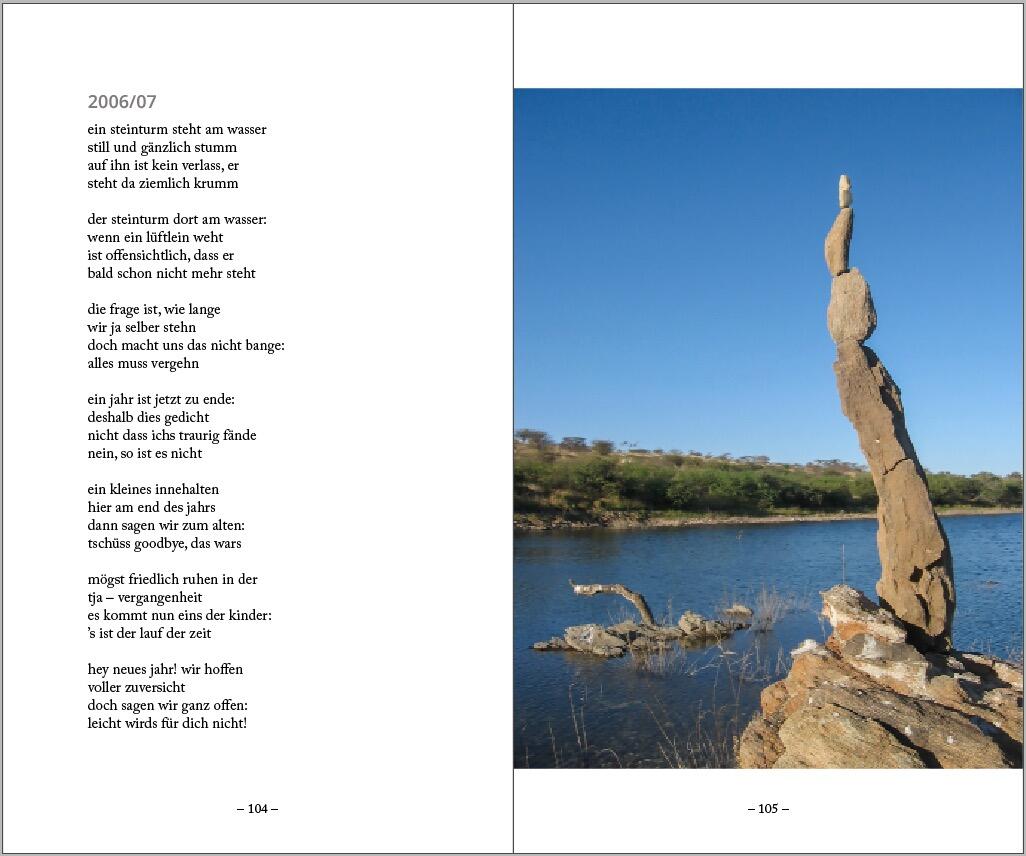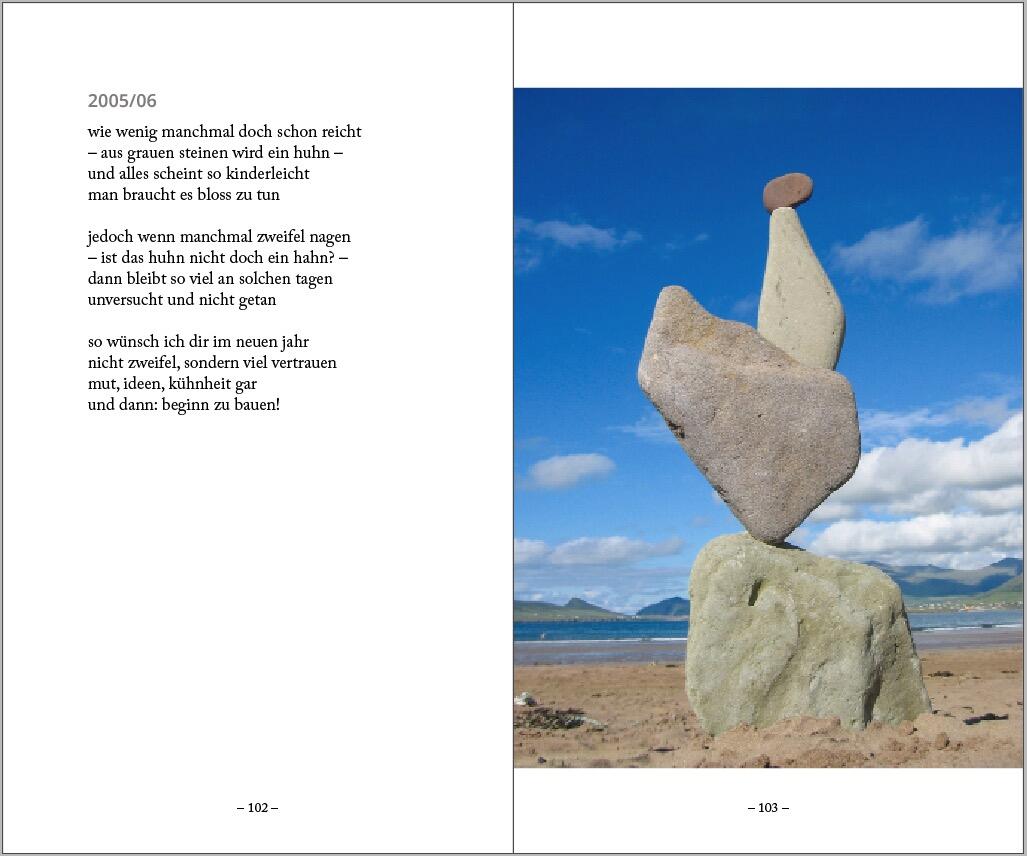
Verschiedene Schriftgrössen in einem Kapitel
Ein Gedichtband wird ein Kapitel mit 30 Gedichten zum Jahreswechsel enthalten. Diese Gedichte unterscheiden sich in ihrer Länge. Sie müssen aber alle je auf einer linken Seite ihren Platz finden. Frage nun: Alle Gedichte in einer Schriftgrösse, auch wenn die "kürzeren" dadurch halt in einer relative kleinen Schrift sind oder zwei Schriftgrössen, die eine für die kürzeren und die andere für die längeren Gedichte.
Als Leser würde ich mich fragen, warum einige Gedichte größer gesetzt sind – sind die wichtiger? Sind das Schlüsselstellen für nachfolgende? Kapiteleinleitungen? Das spräche eher für die durchgehend kleinere Variante.
(An das Fehlen der Versalien könnte ich mich eh nicht gewöhnen, da wäre bei mir schon sehr bald Schluss mit dem Lesen.)